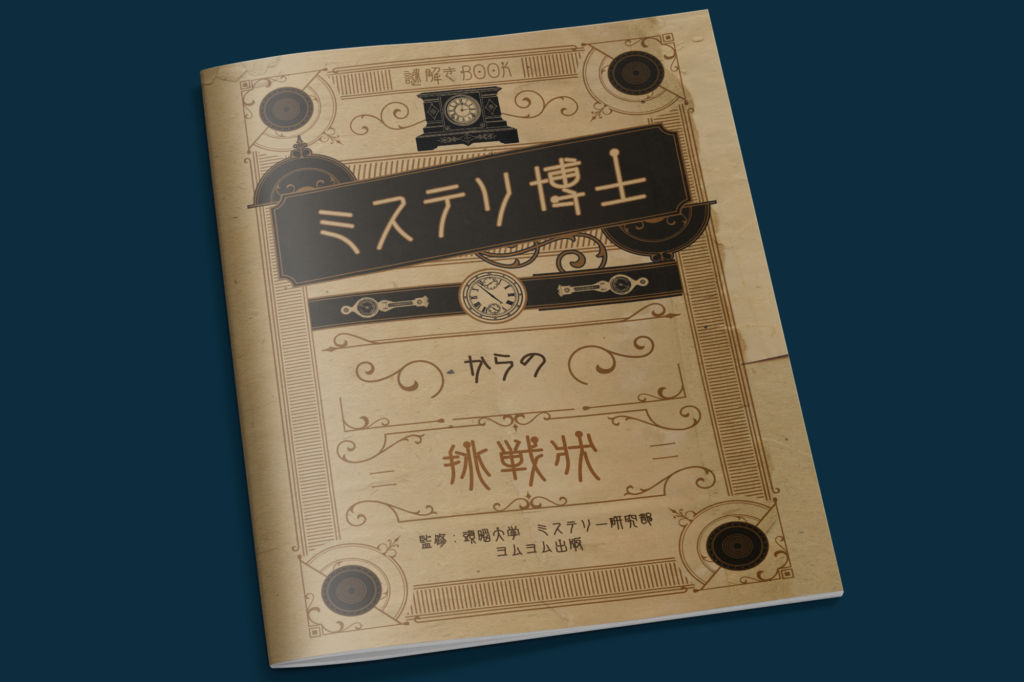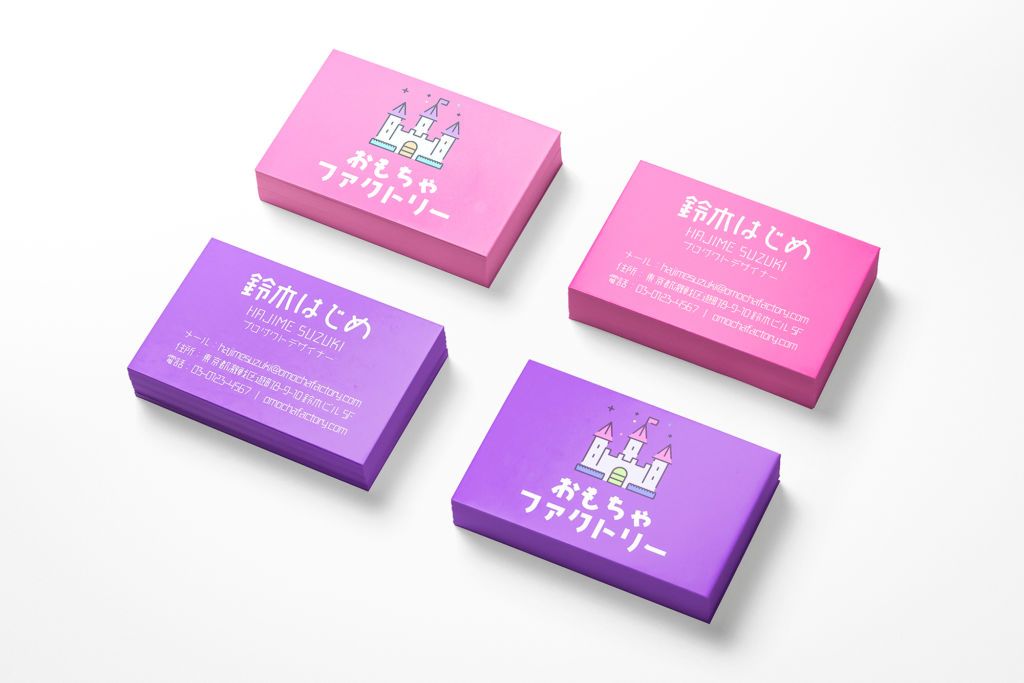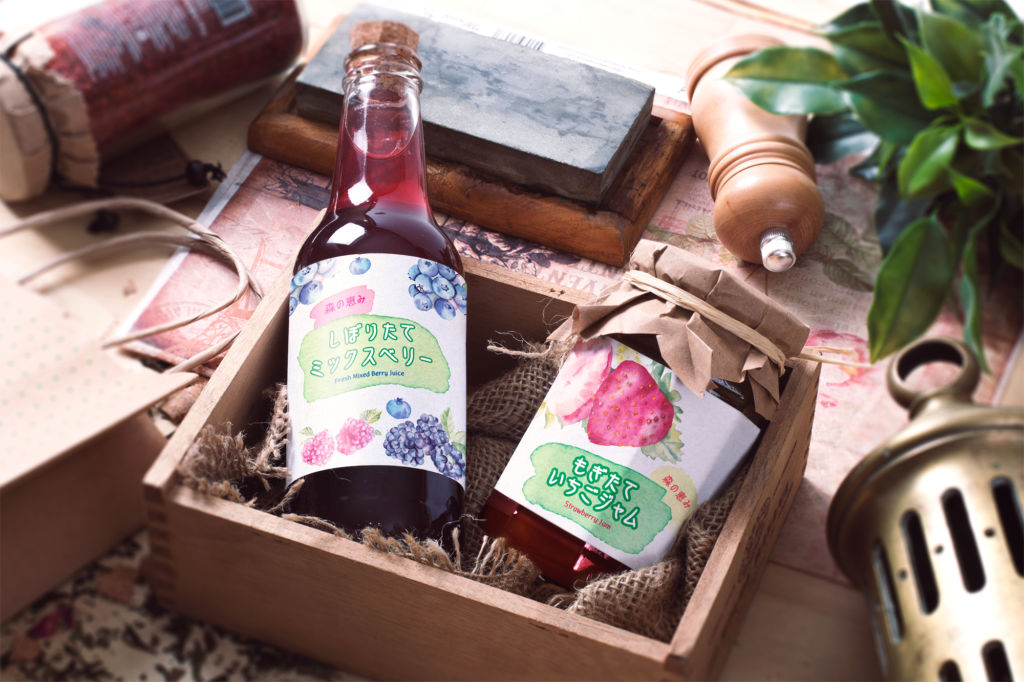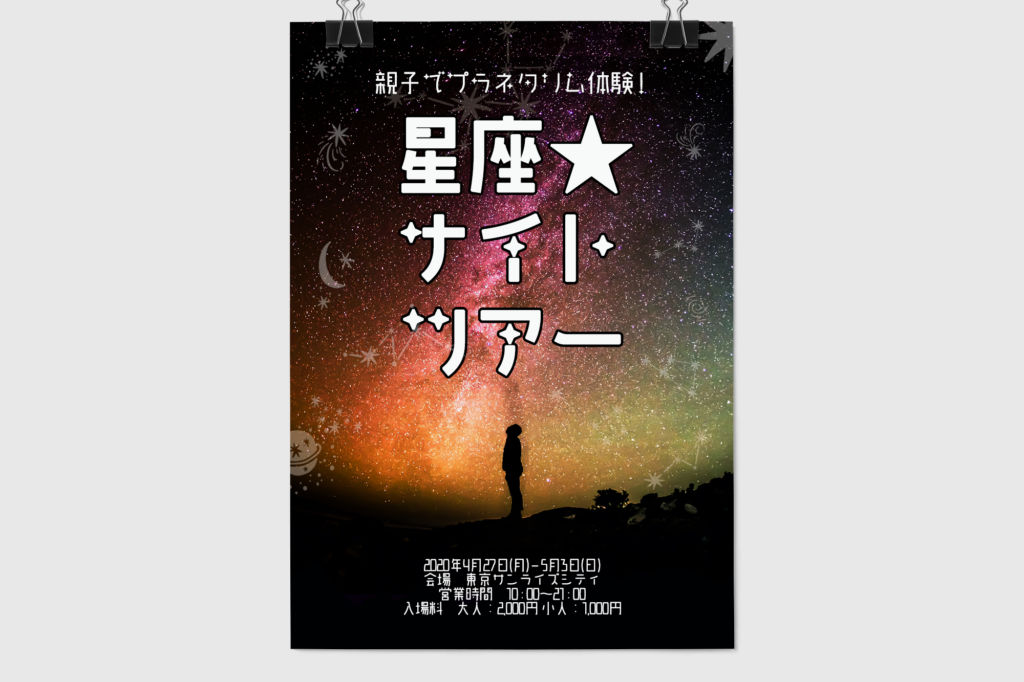
「ときめくレトロな日本語フォント集」の気になる中身
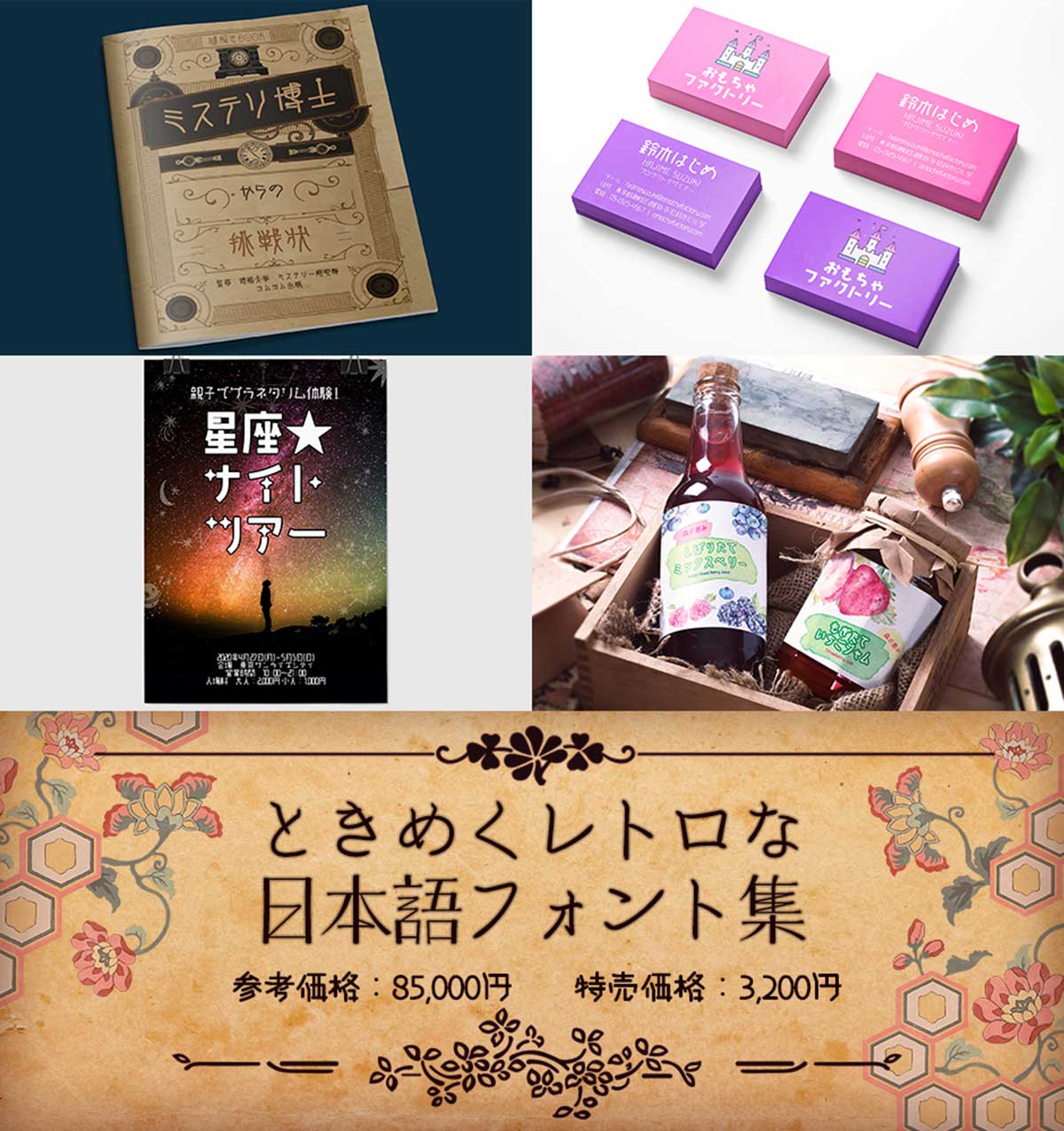
和風デザインフォントパック
「ときめくレトロな日本語フォント集」はポータルアンドクリエイティブ提供の、デザイン性の高い17書体を集めたコレクション。
キュートなかるたシリーズ、かるたシリーズRound版のかるた丸シリーズ、星がアクセントのかるた綺羅シリーズや、篆書体をもとに作られた点篆シリーズ、明治後期をイメージした雛 Oldシリーズ、大正期をイメージした雛 Sweetシリーズなど、あなたのデザインワークを助けてくれるフォントがずらりと揃っています。
- かるたシリーズ
- かるた丸シリーズ
- かるた綺羅シリーズ
- 喜楽丸シリーズ
- 点篆シリーズ
- 組木丸シリーズ
- 雛 Oldシリーズ
- 雛 Sweetシリーズ